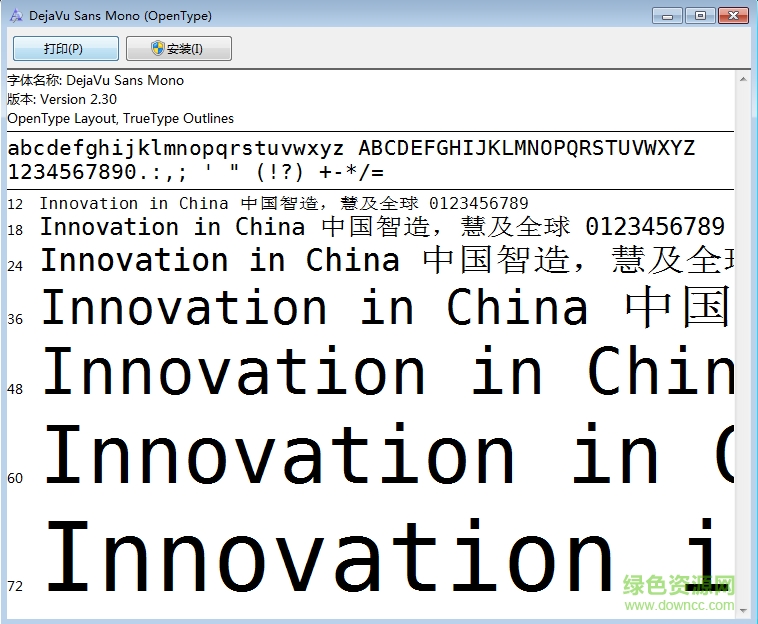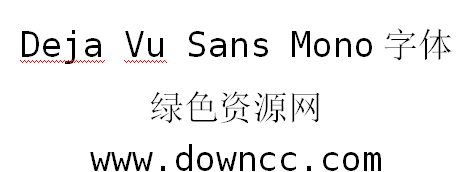
Deja Vu Sans Mono字體
Deja Vu Sans Mono字體是一款清新精簡的網(wǎng)頁字體,讓你的英文輸入更顯端正穩(wěn)重,給人舒適視覺,來綠色資源網(wǎng)即可免費下載使用!
deja vu sans mono字體TTF介紹
Deja Vu Sans Mono以Vera為基礎(chǔ),但是比后者提供更多字符了。適于任何字號,需要anti-aliasing。
Deja Vu Sans Mono在英文輸入上要優(yōu)秀與中文輸入,是較為常用的的十大編程字體之一,使用廣泛,格局和字體間距都很適中。